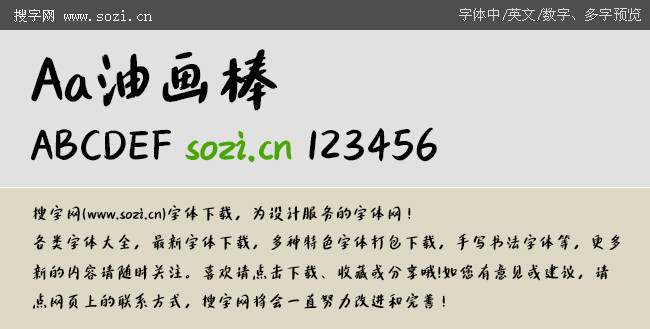
Aa油畫(huà)棒
搜字網(wǎng)給大家提供一款A(yù)a油畫(huà)棒(非商業(yè)使用)中文字體下載,Aa油畫(huà)棒是一款非?蓯(ài)的手寫(xiě)字體,該字體筆觸較為粗實(shí),充滿童真,非常有趣,適合包裝設(shè)計(jì)、書(shū)裝設(shè)計(jì)、海報(bào)設(shè)計(jì)等應(yīng)用(此字體為個(gè)人非商用版,商用可以聯(lián)系QQ:1006760504)。